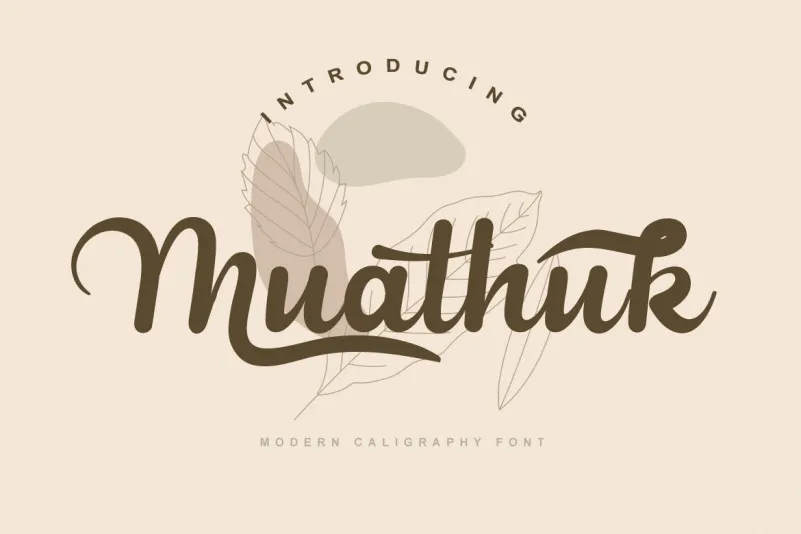
Muathuk Font – Download Grátis
Esta é uma tipografia de escrita áurea, com traços suaves e linhas fluidas que oferecem a essência elegante e sofisticada do estilo cunhado. Ela não só mantém suas influências do cunho clássico, mas também proporciona um toque contemporâneo e fresco para seus projetos. Perfeita tanto para o trabalho diário quanto para projetos de alto nível, essa fonte se destacará em qualquer projeto de escrita. Que tal dar esse toque especial a seu próximo design? Descubra por si mesmo como ela pode transformar sua obra.